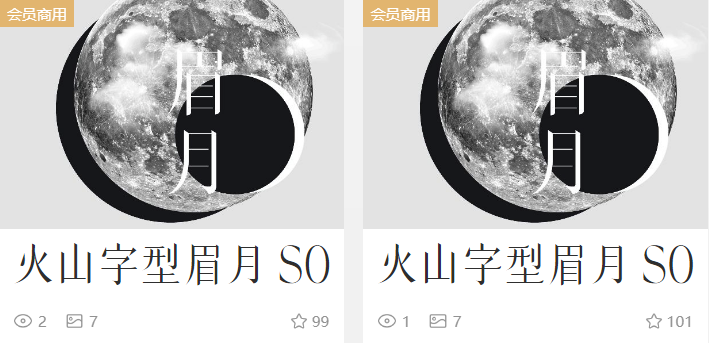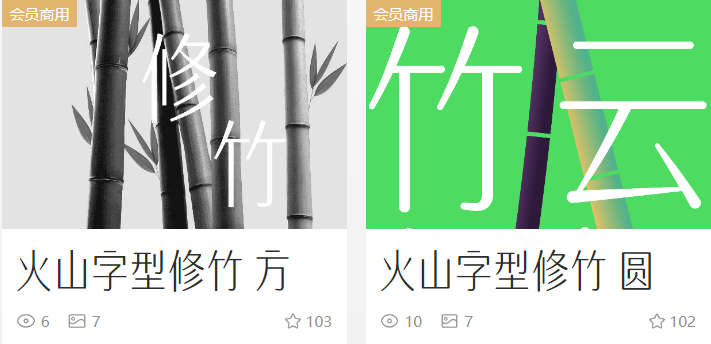
不仅是点字库的字,还增加了一个新的字库品牌,没错,它就是火山字型!
它是由一位从业多年的平面设计师创建,每套字体的风格皆来自日常设计需求,2020年6月1日正式发行了三套原创中文字型——眉月、悍石、修竹,这次都上了会员字体。
一共五款,每款都很有特点,实用性很强。
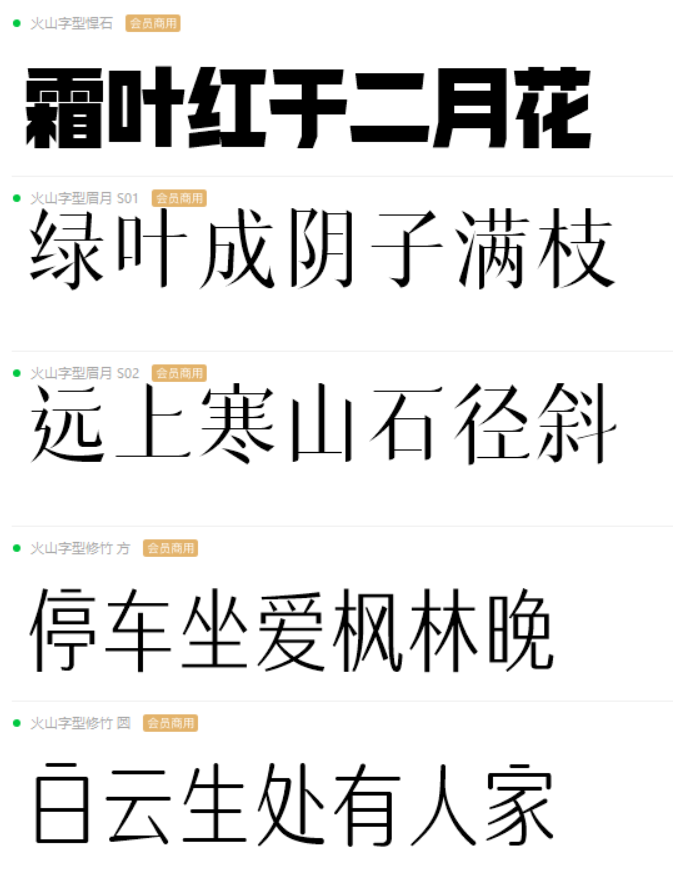
来看看它的展示效果~
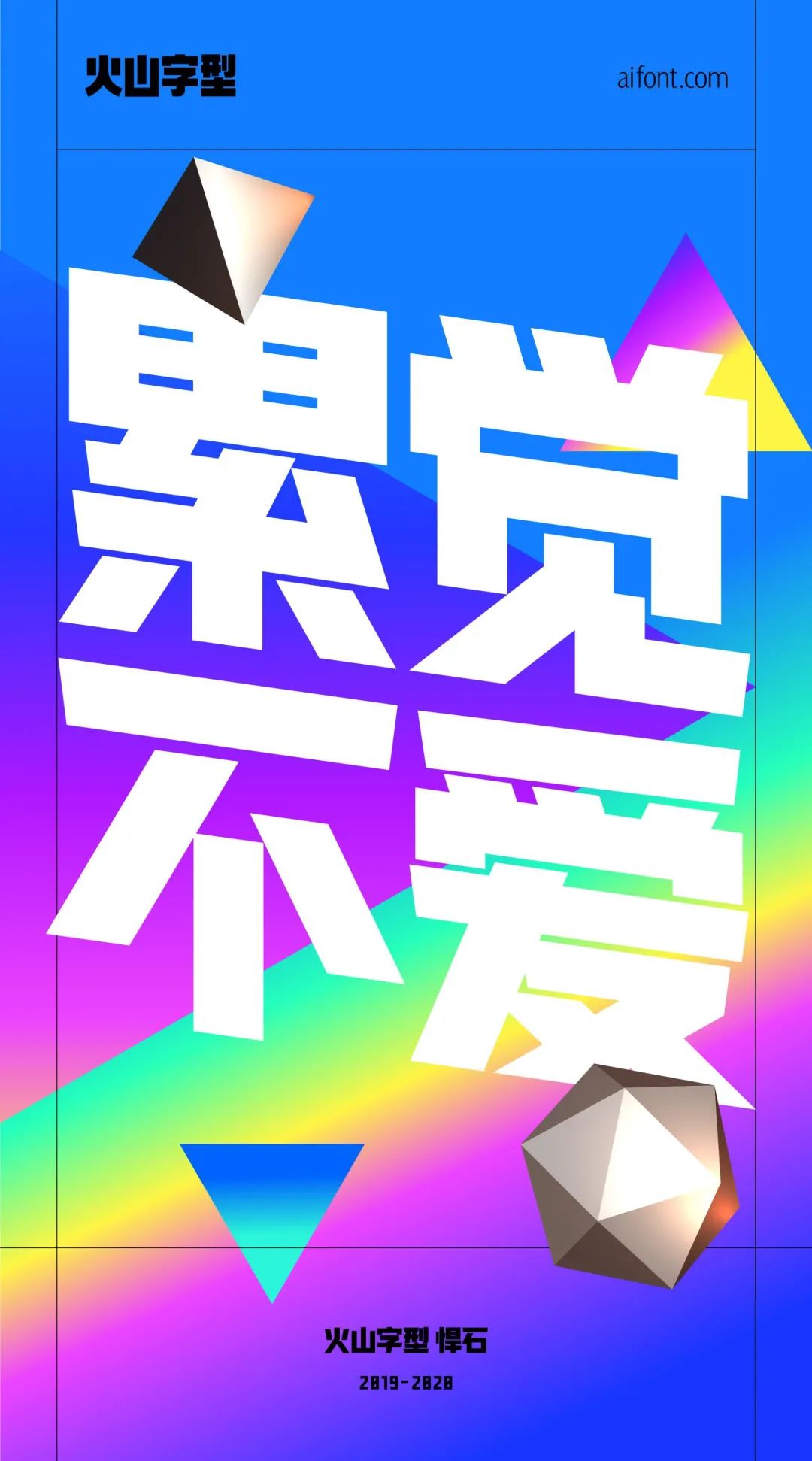
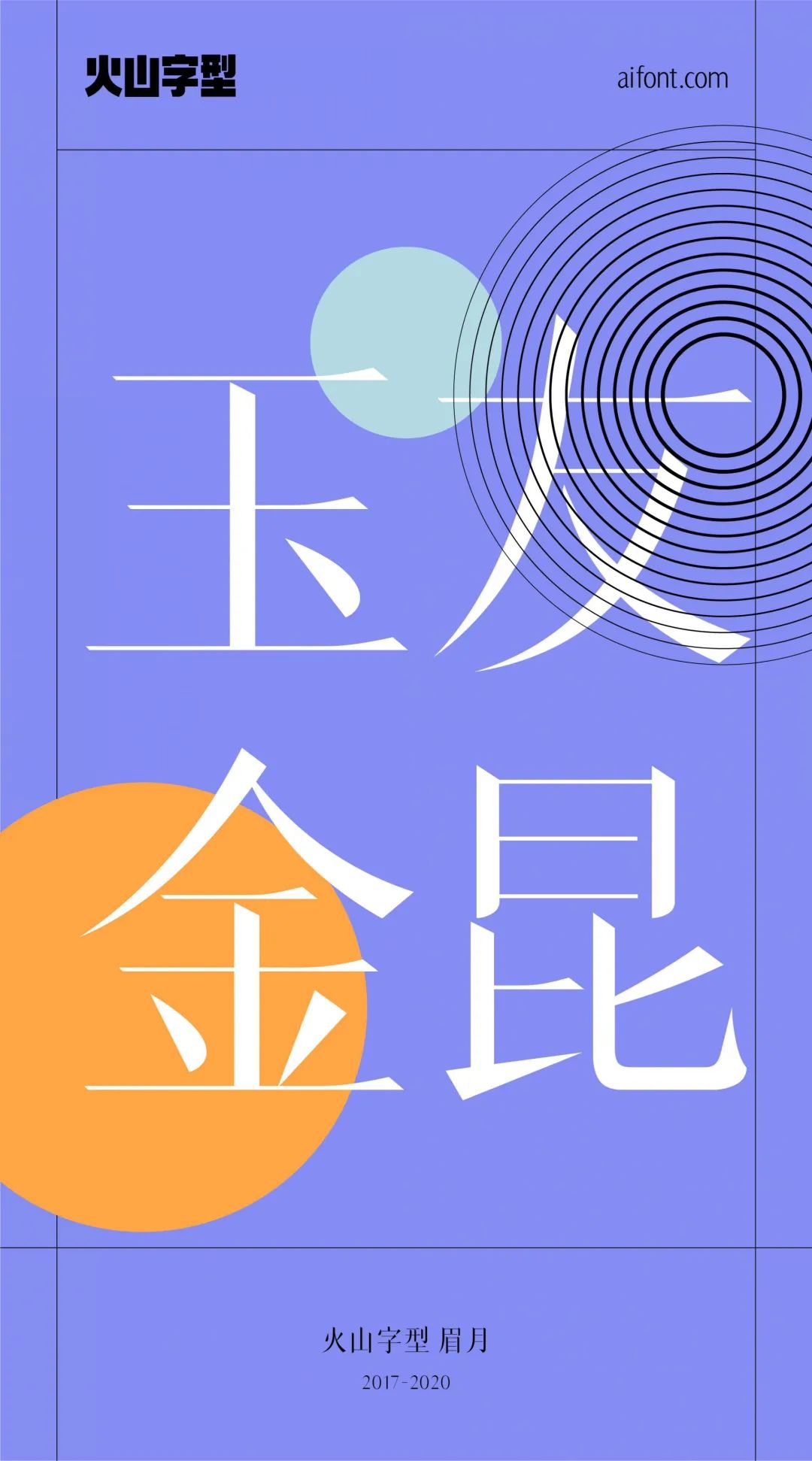
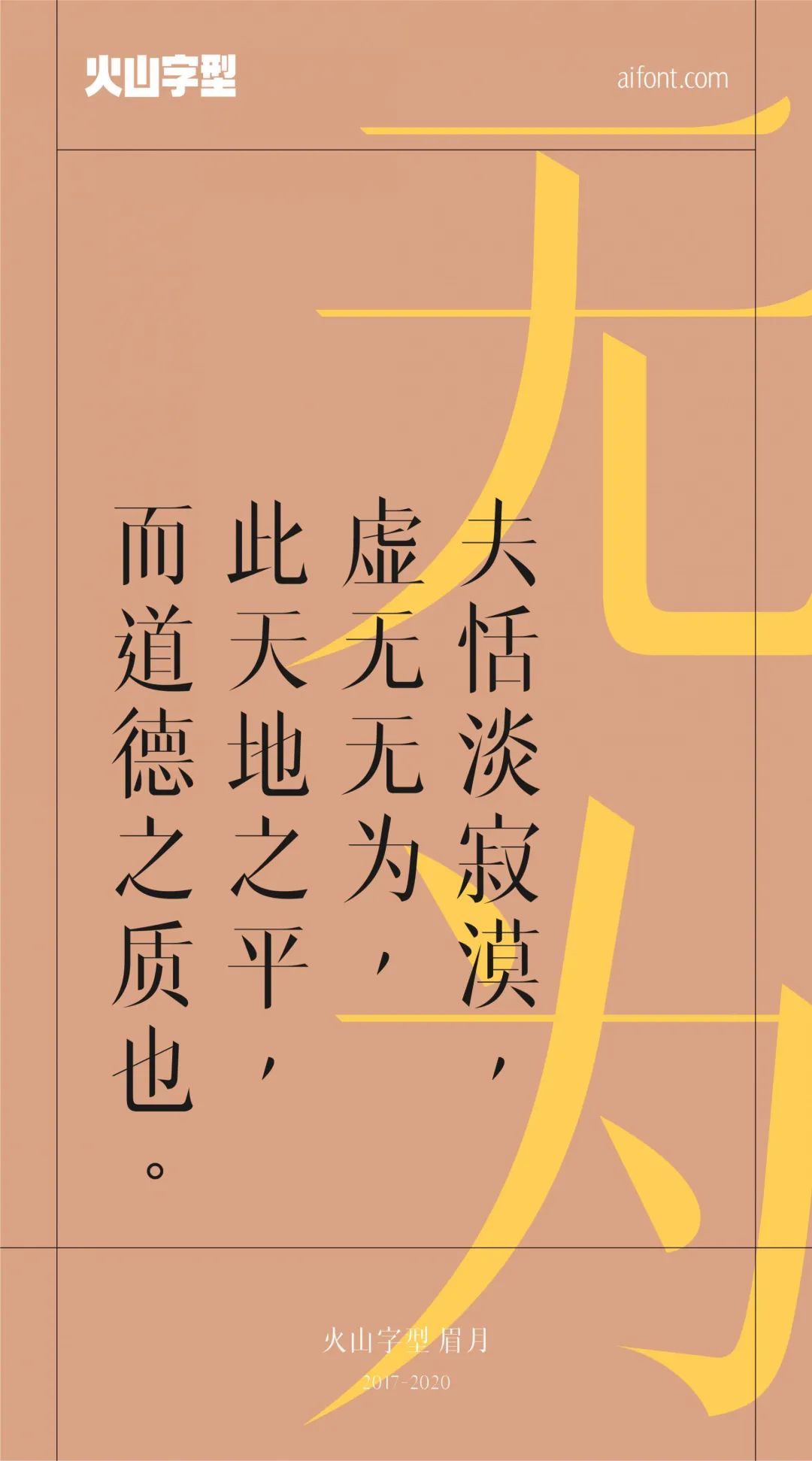
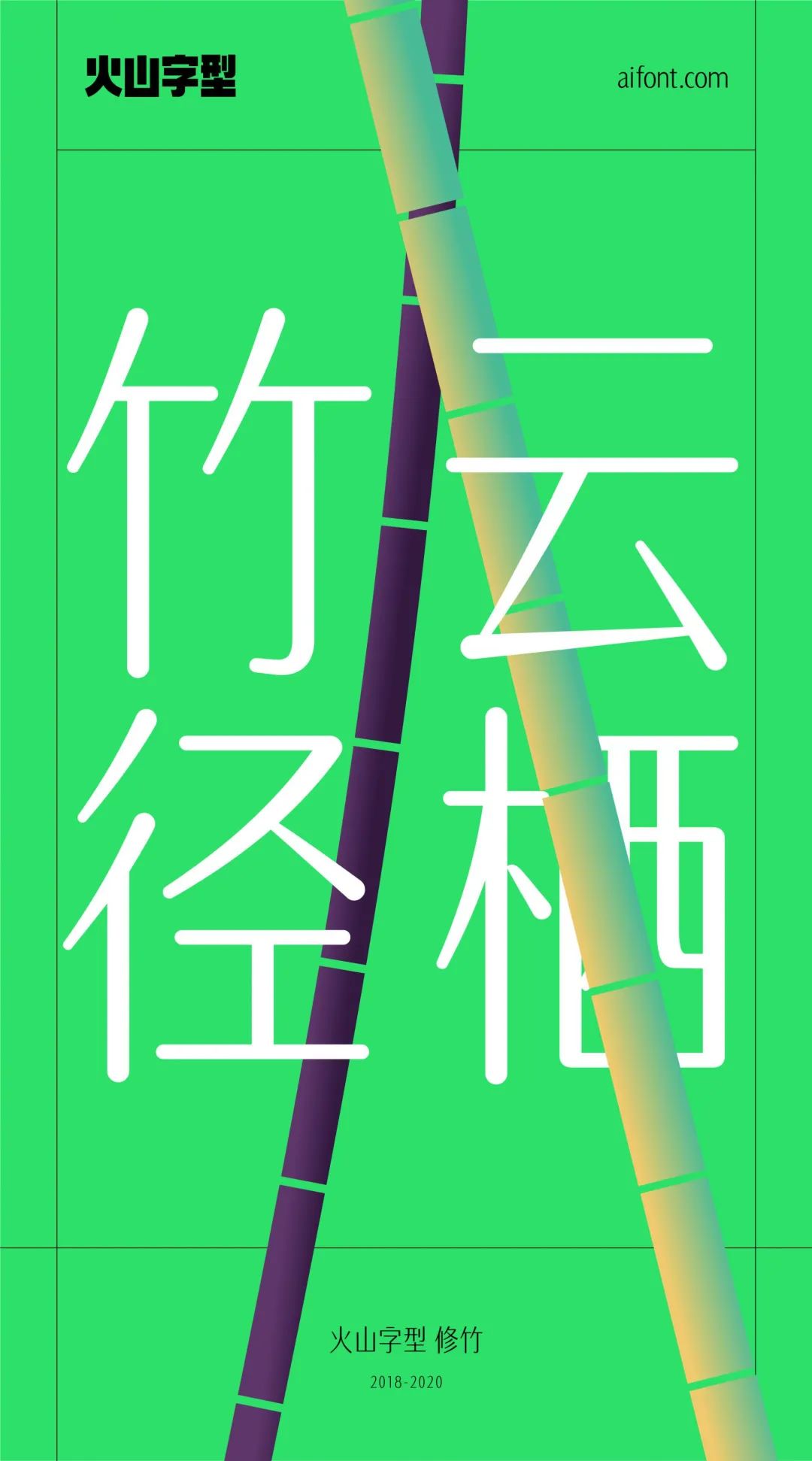
很不错吧?有霸气外露,也有岁月静好,满足你的多种使用场景。另外,柚子细细算了下,包括火山字型在内,现在会员字体已经有14个字体品牌了,以后还会不断增加……